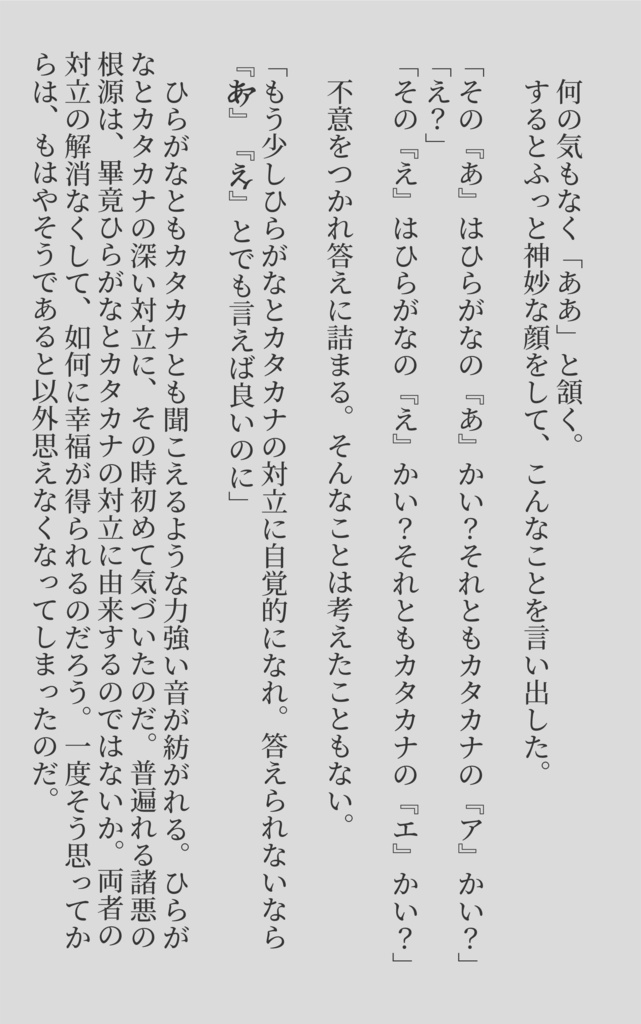
異端仮名 - ひらがな×カタカナ融合字体のフリーフォント
——令和に異端字現る—— ひらがなとカタカナの融合した「異端仮名」が誕生。ひらがなとカタカナの対立に新風を吹き込みます。無料で商用非商用問わずご利用いただけます。 【こんな人にオススメ】 ・異形の文字にわくわくする人 ・ひらがなとカタカナの融合を願う人 ・ひらがなとカタカナ両方一度に使いたい人 【こんなシーンで使えます】 ・可読性の高い狂字が欲しいとき。ひらがなとカタカナが混ざっているだけなので読解に困難がありません。 ・ひらがな表記かカタカナ表記か迷ったとき。 ・日本語を教えるとき。異端仮名を覚えればひらがなカタカナ両方読めます(実証例無し) ・狂人のセリフを書きたいとき(画像4枚目|夢野久作『ドグラ・マグラ』の一節を参照)。
仕様
無連絡で商用利用可能です。改変はできません。 ひらがな、カタカナに同一の字形を当てています。句読点および伸ばし棒(ー)は縦書きに対応しています。 Regular/ExtraBoldの2ウェイトを同梱しています。投げ銭版は無料版と全く同一です。お気をつけください。 投げ銭を検討される方は、下記のフォントをご購入くださいますことも大変励みになります。 ・欧文/カタカナフォント CORORIN https://fontring.booth.pm/items/871969 ・欧文フォント Lemonin https://fontring.booth.pm/items/1156944 作ったフォントが使われているのを見るのが好きです。作品を投稿する際にタグ「#異端仮名」をつけたりクレジットに記載したりしていただくと見つけやすいので嬉しいです😉 このフォントを紹介される際、Boothのサンプル画像は自由にご利用ください。 フォントのバージョンアップのお知らせはこちらで投稿します。フォローお願いします🙏 https://www.pixiv.net/fanbox/creator/31276656